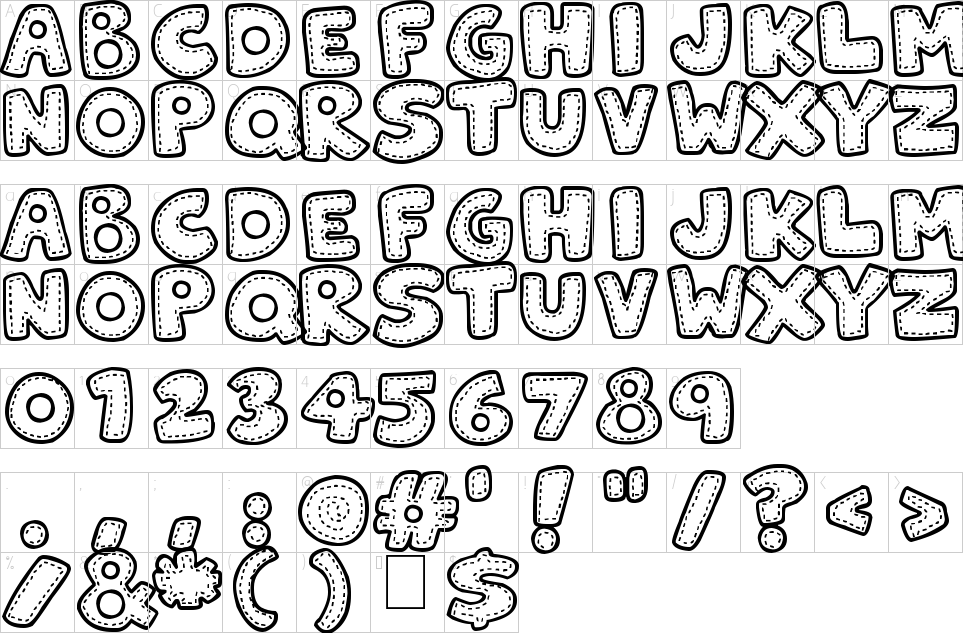
A fonte Patchwork Stitchlings é uma peça de arte visual que se tornou uma fonte grata, disponível para download tanto para Windows quanto para Mac. Desenvolvida por Darrell Flood, Patchwork Stitchlings oferece um charme único e elegante com sua estrutura de linhas que imitam a delicada artesanal de costura de patchwork. Suas linhas suaves e precisas complementam perfeitamente a estética de várias aplicações, como projetos de design gráfico, criação de materiais de impressão ou até mesmo como um toque refinado para seu site pessoal. Com seu design agradável e fácil de ler, Patchwork Stitchlings é uma fonte grata que adoraríamos ver em mais projetos.